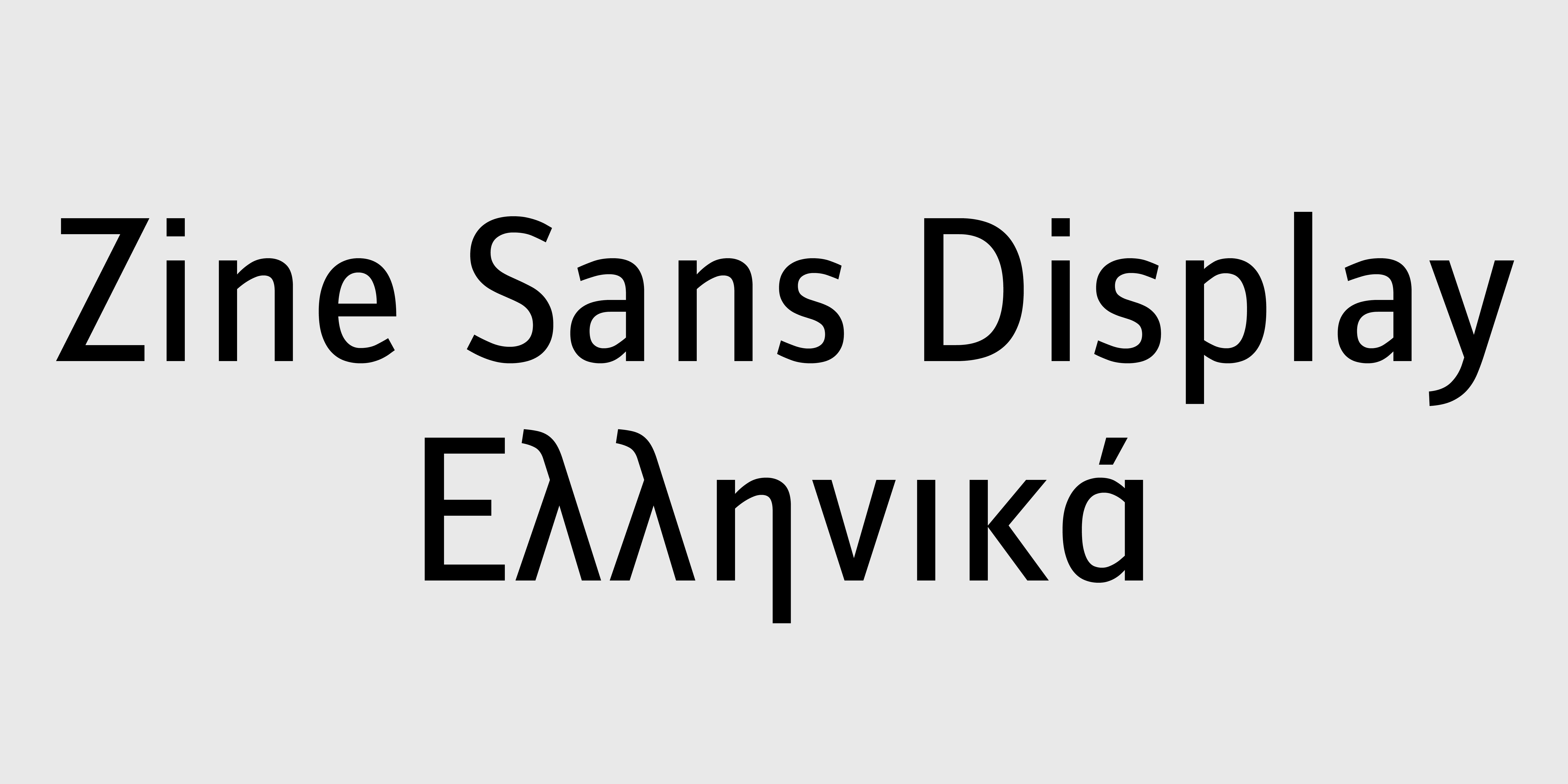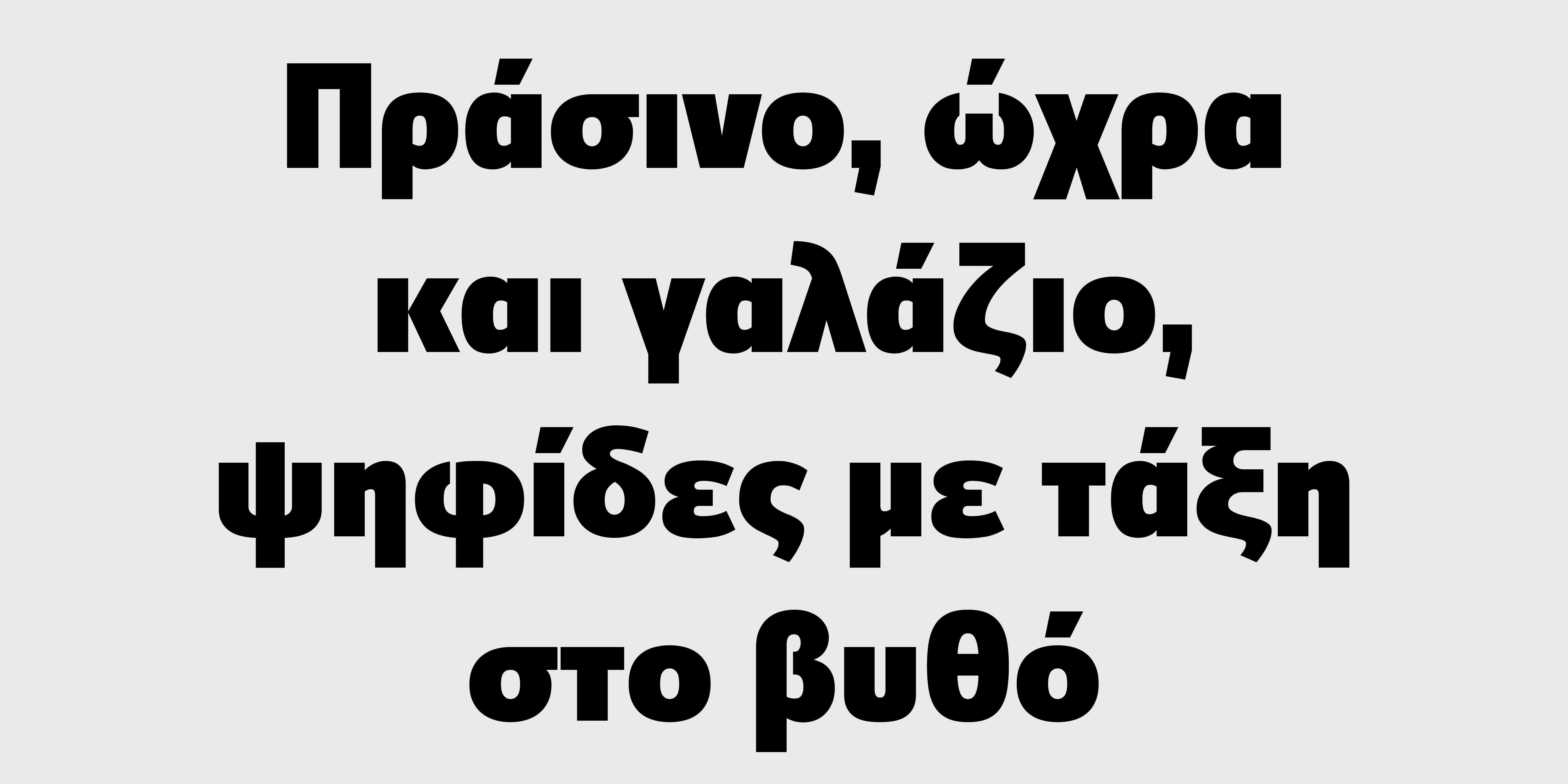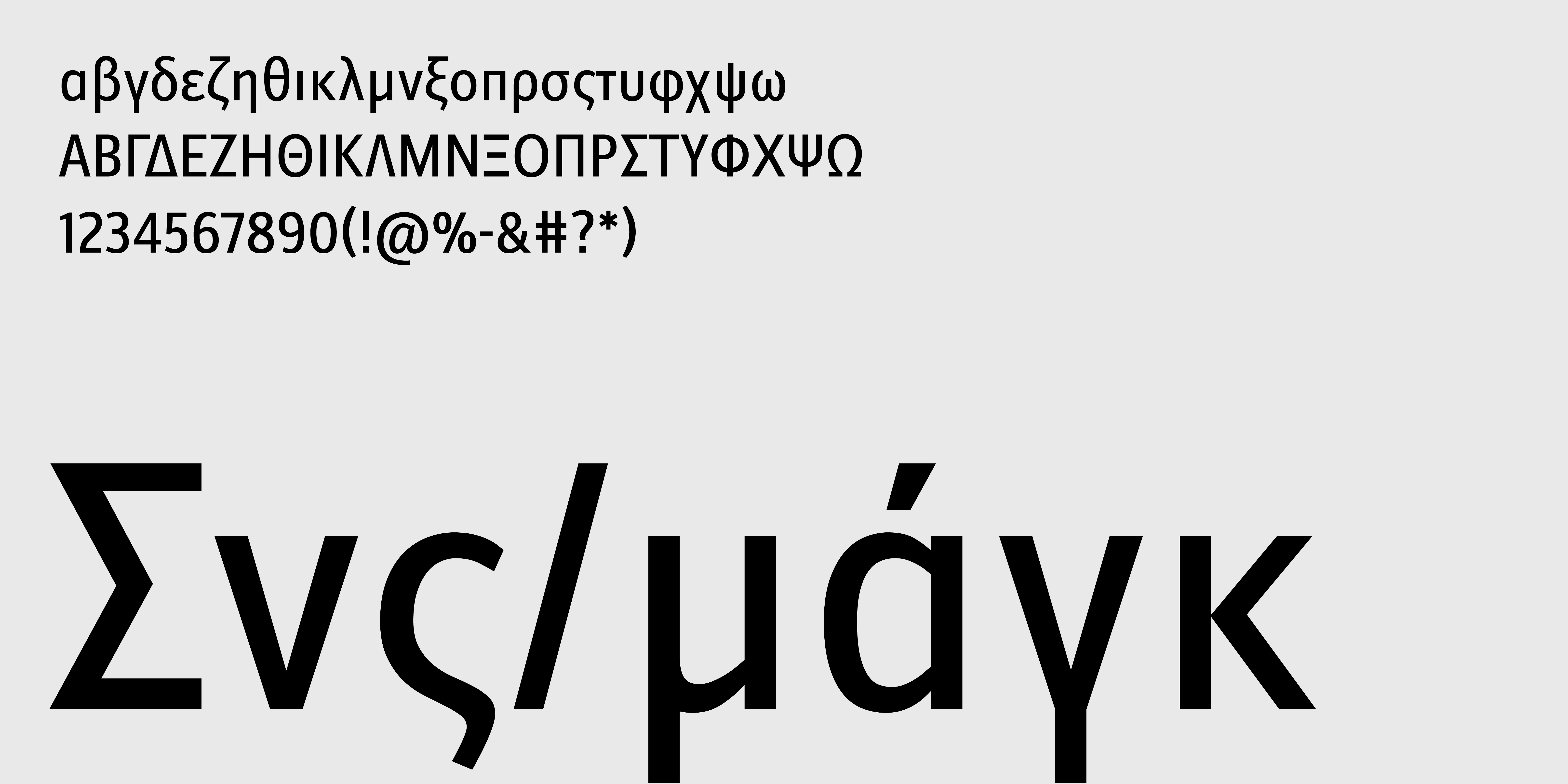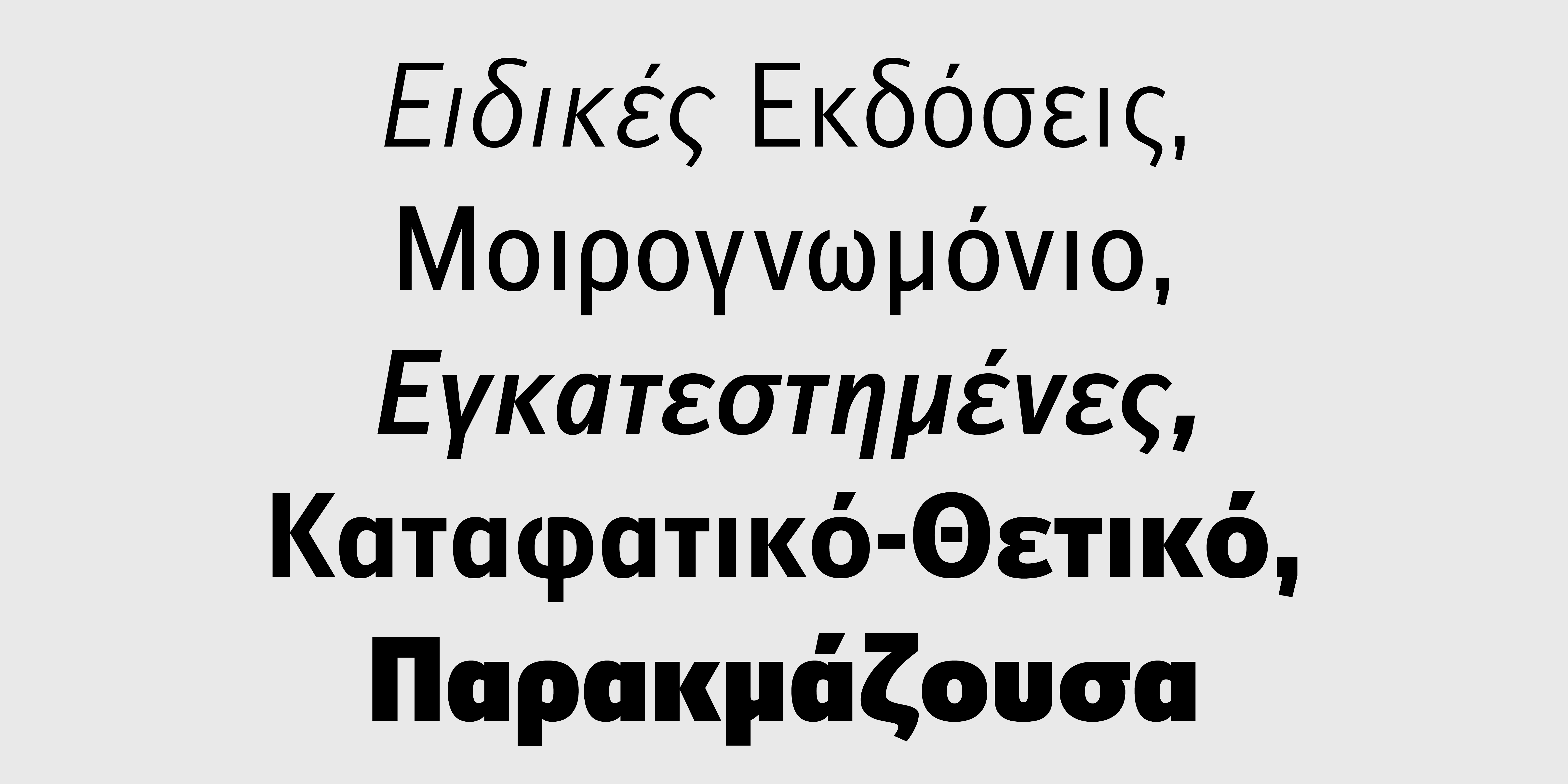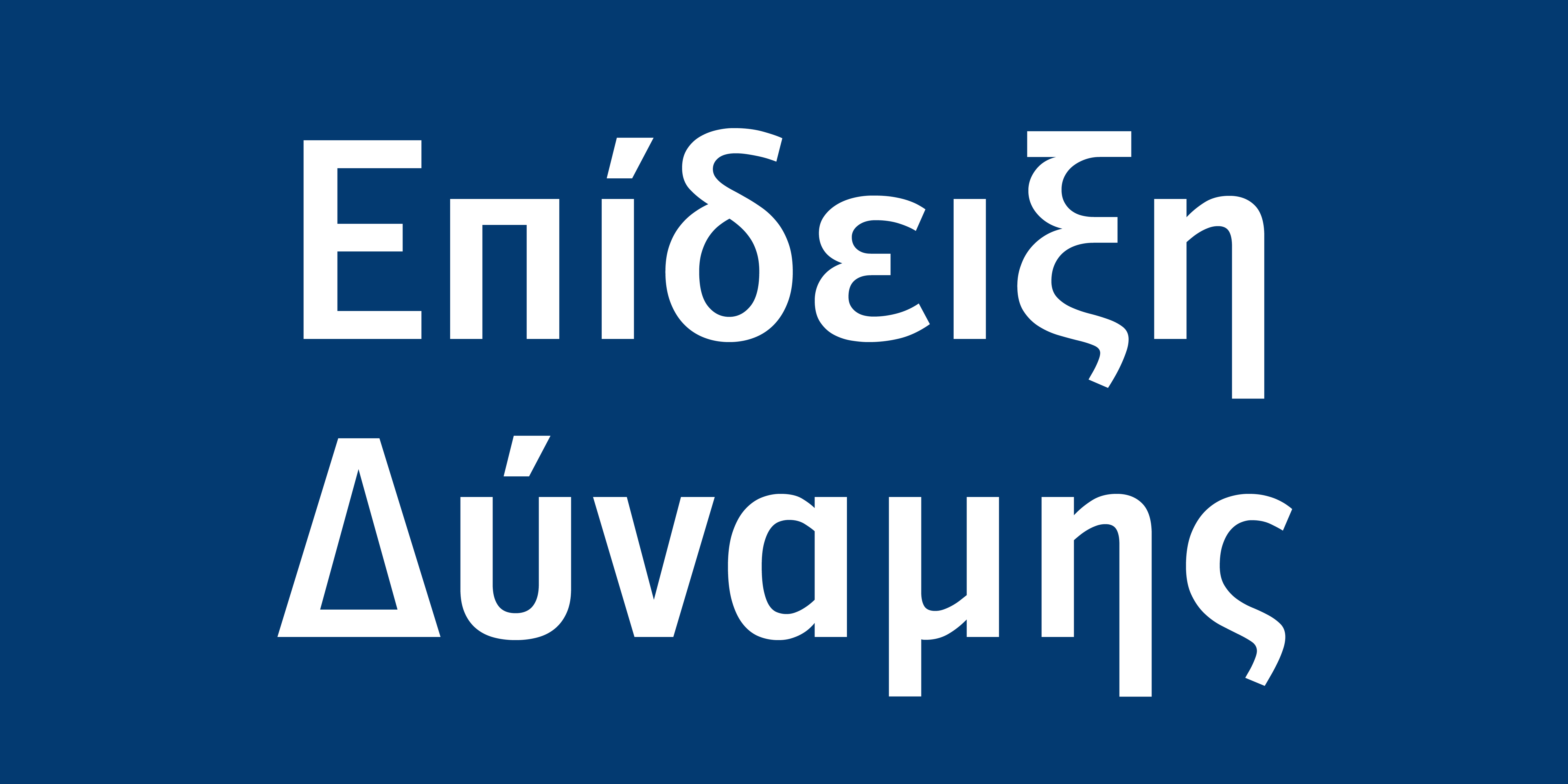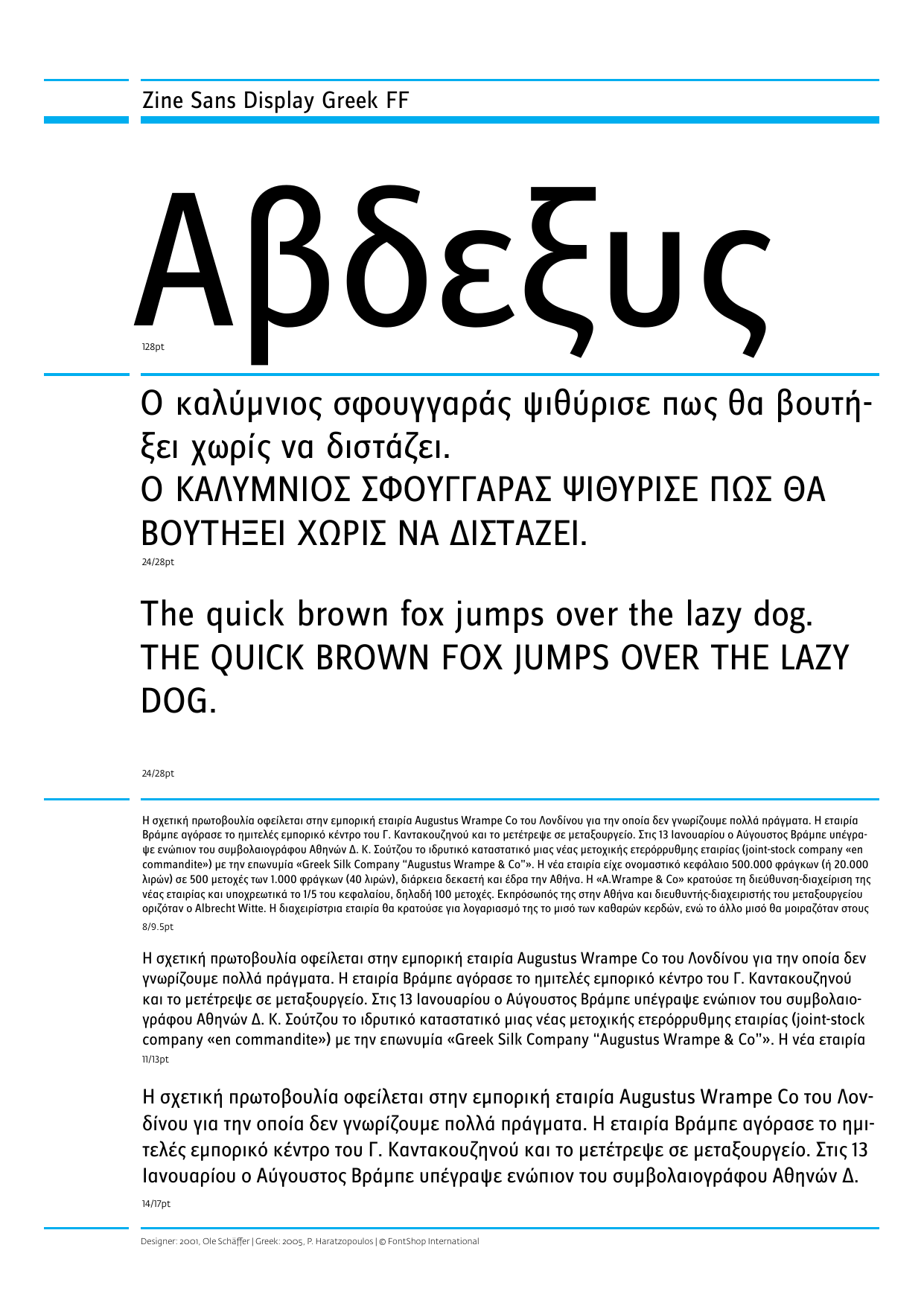
Zine Sans Display Ελληνικά
Η βάση για τη δημιουργία της Zine ήταν μία γραμματοσειρά τίτλων που είχε σχεδιαστεί για τη Γερμανική εφημερίδα Sächsische Zeitung γύρω στο 1996/97. Αυτή όμως ήταν μόνο η αρχή. Ο Ole Schäfer ξανασχεδίασε από την αρχή τη γραμματοσειρά βελτιώνοντας τις φόρμες των γραμμάτων και προσθέτοντας νέα βάρη. Η προσπάθειά του αυτή έγινε με γνώμονα να λυθεί ένα πρόβλημα που αντιμετωπίζουν συχνά οι γραφίστες στο σχεδιασμό εφημερίδων και περιοδικών, να έχουν δηλαδή μία γραμματοσειρά με πατούρες και μία χωρίς, που να λειτουργούν μαζί στους τίτλους. Η λύση που πρότεινε ήταν να σχεδιάσει εξ’αρχής: μία serif, μία sans serif και μία slab serif (η slab δεν διατίθεται στα ελληνικά); - που αυτός ο συνδυασμός να καλύπτει ένα ευρύ φάσμα αναγκών στο σχεδιασμό. Ως γραμματοσειρές τίτλων, οι Zines ταιριάζουν καλύτερα σε επικεφαλίδες, τίτλους, υπότιτλους, λεζάντες φωτογραφιών κλπ. ενώ με λίγο χαλαρότερο spacing λειτουργούν πολύ καλά και σε κείμενο. Η ελληνική Zine Sans σχεδιάστηκε για να συνοδέψει τη Zine Serif που είχε αρχικά σχεδιαστεί για την εφημερίδα «Απογευματινή».